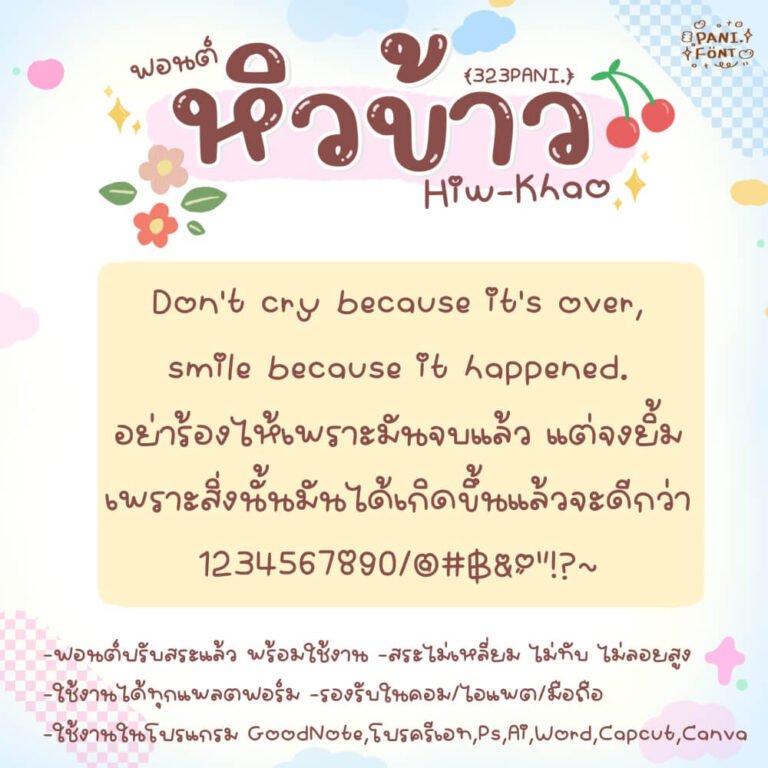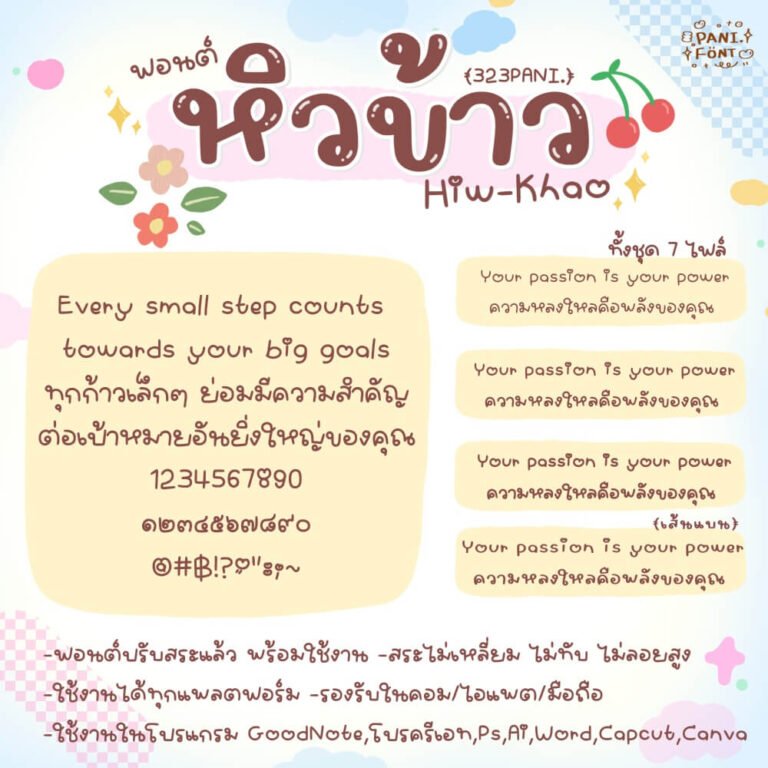
หิวข้าว (323PANIHiwKhao)
ฟอนต์หิวข้าว โหลดใช้ฟรีตัว Demo – ชุดนี้ตั้งใจเขียนแนวบาง ตัวชิดหน่อย ให้อารมณ์เขียนเอง เขียนสด ตัวอักษรจะดุ๊กดิ๊กนิดๆ (แอนทำไฟล์หนา กับเส้นแบน และชุดช่องไฟกว้างเพิ่มให้ด้วยค่ะ)
ชุดนี้จะแต่งภาพง่าย ทำคลิปน่ารัก ไม่จำเจ แต่ยังคง อ่านง่าย สบายตา สไตล์แอนค่ะ